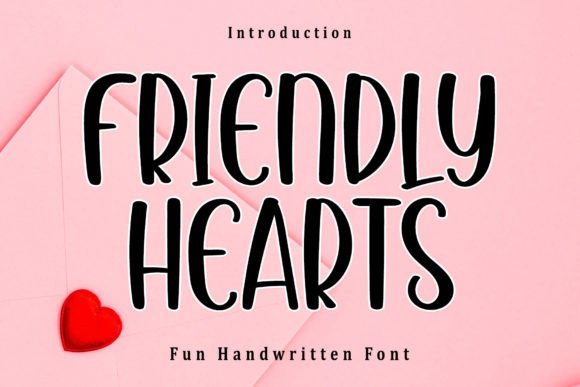
Friendly Hearts
適切なデザイン要素を見つけるのは難しい場合がありますが、Friendly Heartsは作品を即座に引き立てる優れたコレクションを提供します。
POD(オンデマンド印刷)製品、結婚式の招待状、またはソーシャルメディアのグラフィックを作成している場合でも、Friendly Heartsは理想的です。